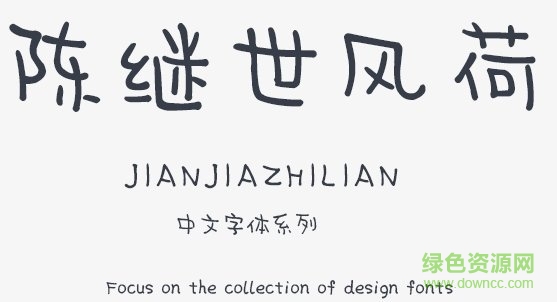
陳繼世風(fēng)荷體是一款作者新推出的一款手寫字體,文風(fēng)干凈字跡清晰,給人賞心悅目的視覺(jué)體驗(yàn),讓你的書寫和設(shè)計(jì)更有個(gè)性特色,綠色資源網(wǎng)誠(chéng)意推薦!
陳繼世風(fēng)荷體是一款適合手寫藝術(shù)設(shè)計(jì)的字體,字庫(kù)完整,有著極佳的視覺(jué)體驗(yàn),因此可以在很多領(lǐng)域廣泛使用,給你的平面設(shè)計(jì)帶來(lái)更多特色魅力!